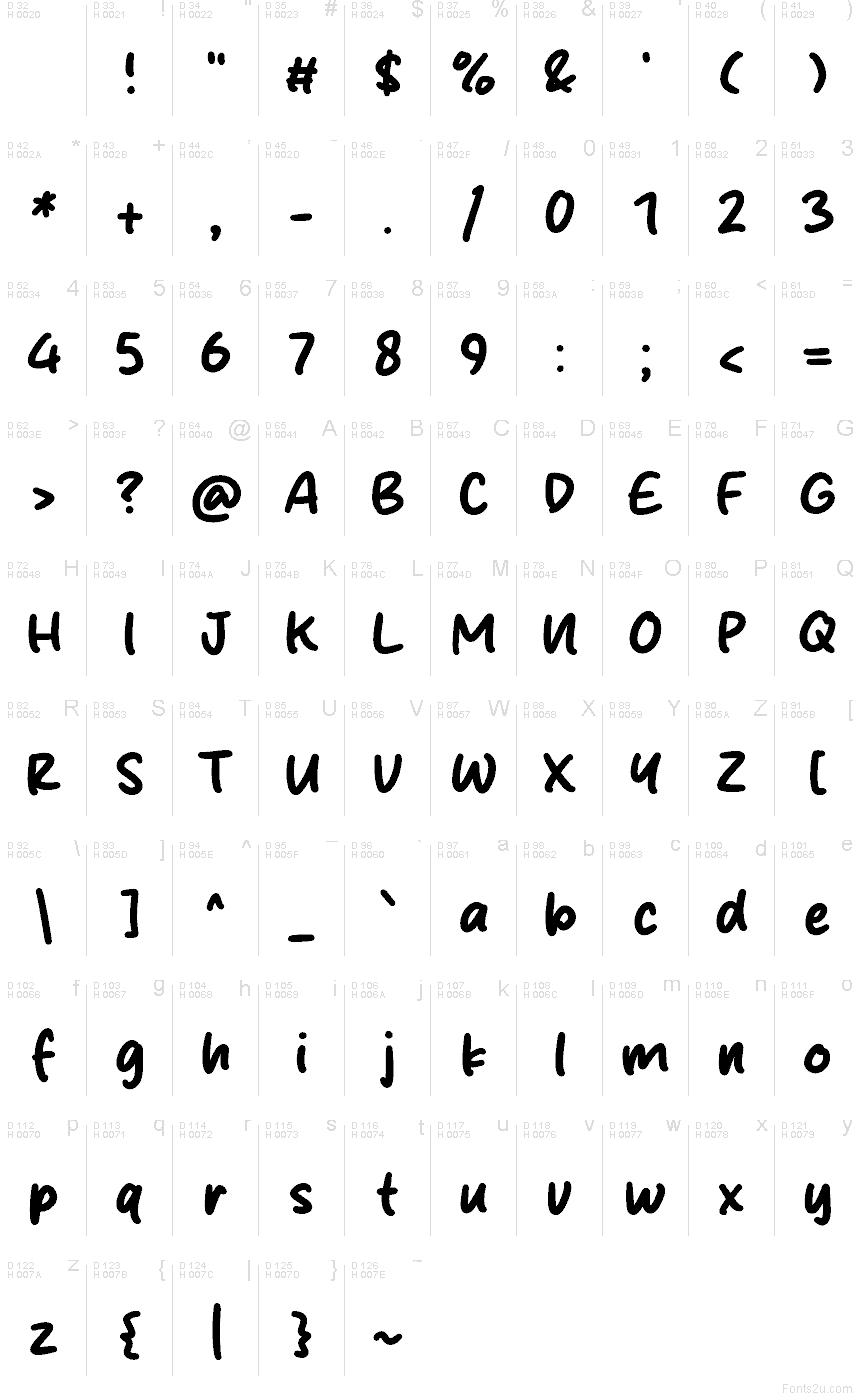
Study Daily di MJType è un carattere brush script gratuito con un tocco casual, perfetto per le note prese a lezione. Le lettere sono spesse, arrotondate e fluide, con un ritmo leggermente vivace, giunture morbide e tratti discendenti ad anello che lo rendono amichevole piuttosto che rifinito.
Si adatta naturalmente a copertine di quaderni, pianificatori, insegne di caffè, post di citazioni e anteprime YouTube, dove un font gratuito deve sembrare scritto a mano senza risultare complicato. Poiché i tratti rimangono ampi e semplici, funziona bene anche per titoli brevi, targhette e branding in stile adesivo che punta a una voce calda e informale.